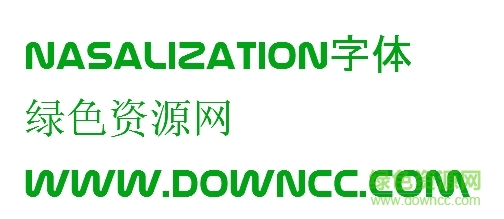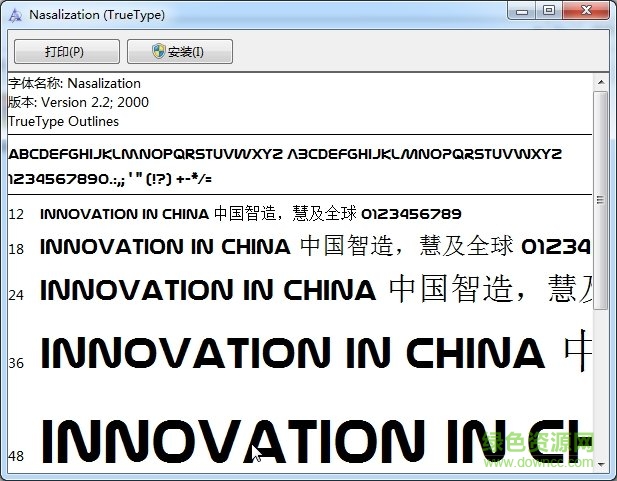
Nasalization是一款造型獨(dú)特的海報(bào)字體,有著清晰大方的視覺呈現(xiàn),圓潤柔和的造型讓你的文字更加生動(dòng),綠色資源網(wǎng)歡迎極大下載nasalization系列字體!
Nasalization Regular
Nasalization 3D Regular
Nasalization Bold Version
nasalization extended bold
Nasalization Video Regular
Nasalization Galaxy Regular
Nasalization Ink Regular等
nasalization字體是一款有著很強(qiáng)展現(xiàn)力的英文字體,與眾不同的設(shè)計(jì)讓你的文字更加鮮活,在藝術(shù)設(shè)計(jì)、排版印刷、海報(bào)制作等領(lǐng)域使用較廣!